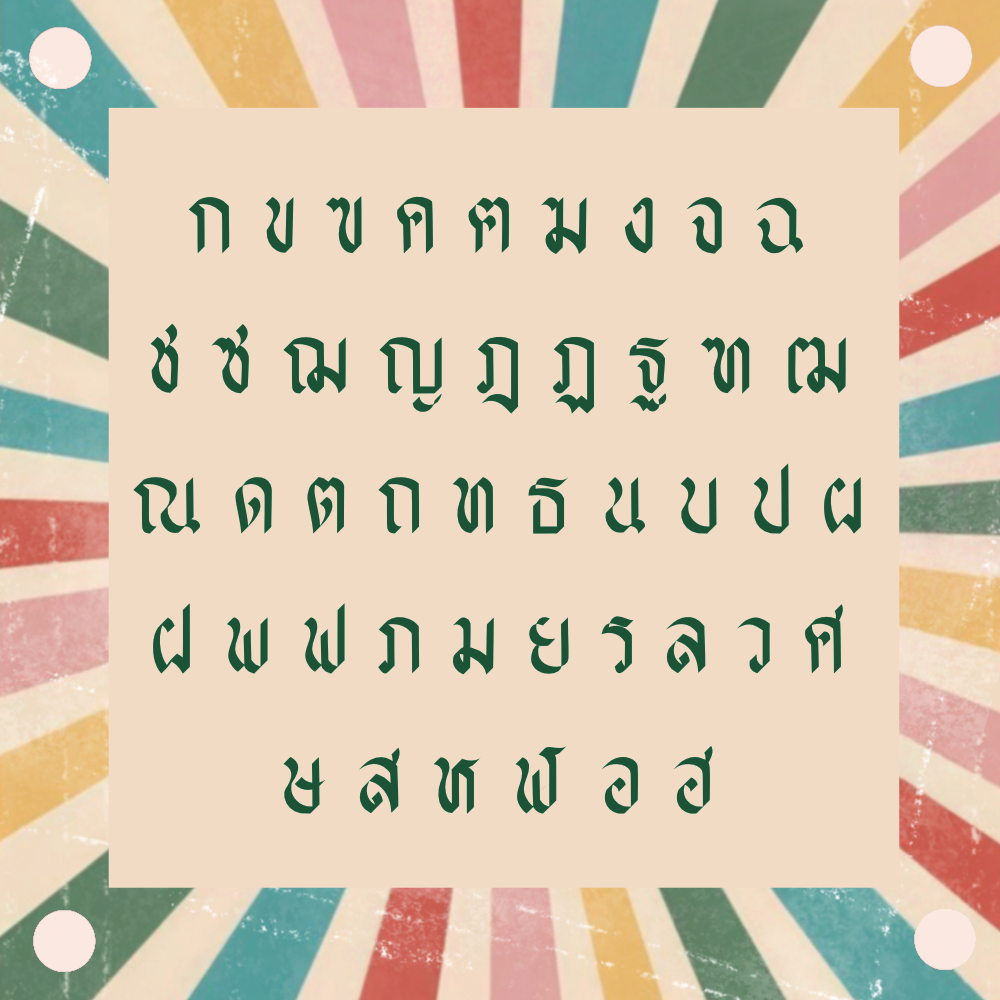
ทอศิลป์ร่ำรวย
ฟอนต์นี้เอาฟอนต์ ทอศิลป์จงเจริญ มาปรับให้ผอมลง
แล้วเปลี่ยนบางสิ่งนิดบางสิ่งหน่อย เล็กๆ น้อยๆ
ตั้งชื่อเป็นมงคลรับปีใหม่ 2568
ฟอนต์  "ทอศิลป์ร่ำรวย"